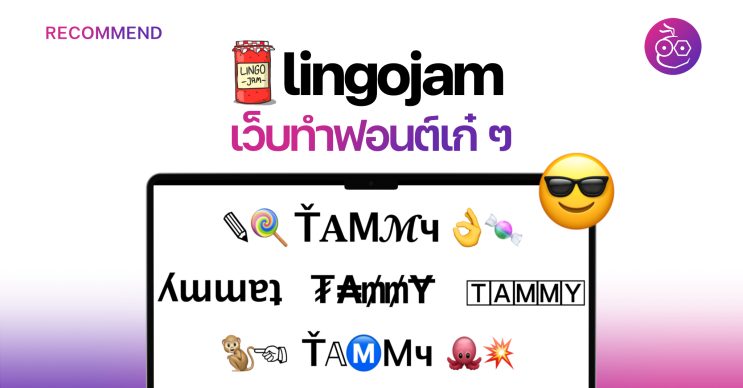
ใครที่เบื่อกับฟอนต์ตัวอักษรแบบเดิม ๆ ต้องลองใช้ lingojam เว็บนี้จะทำฟอนต์เก๋ ๆ ออกมาให้เราใช้ แถมยังดูแปลกใหม่สุด ๆ!
lingojam เว็บทำฟอนต์เก๋ ๆ ไว้ใช้!
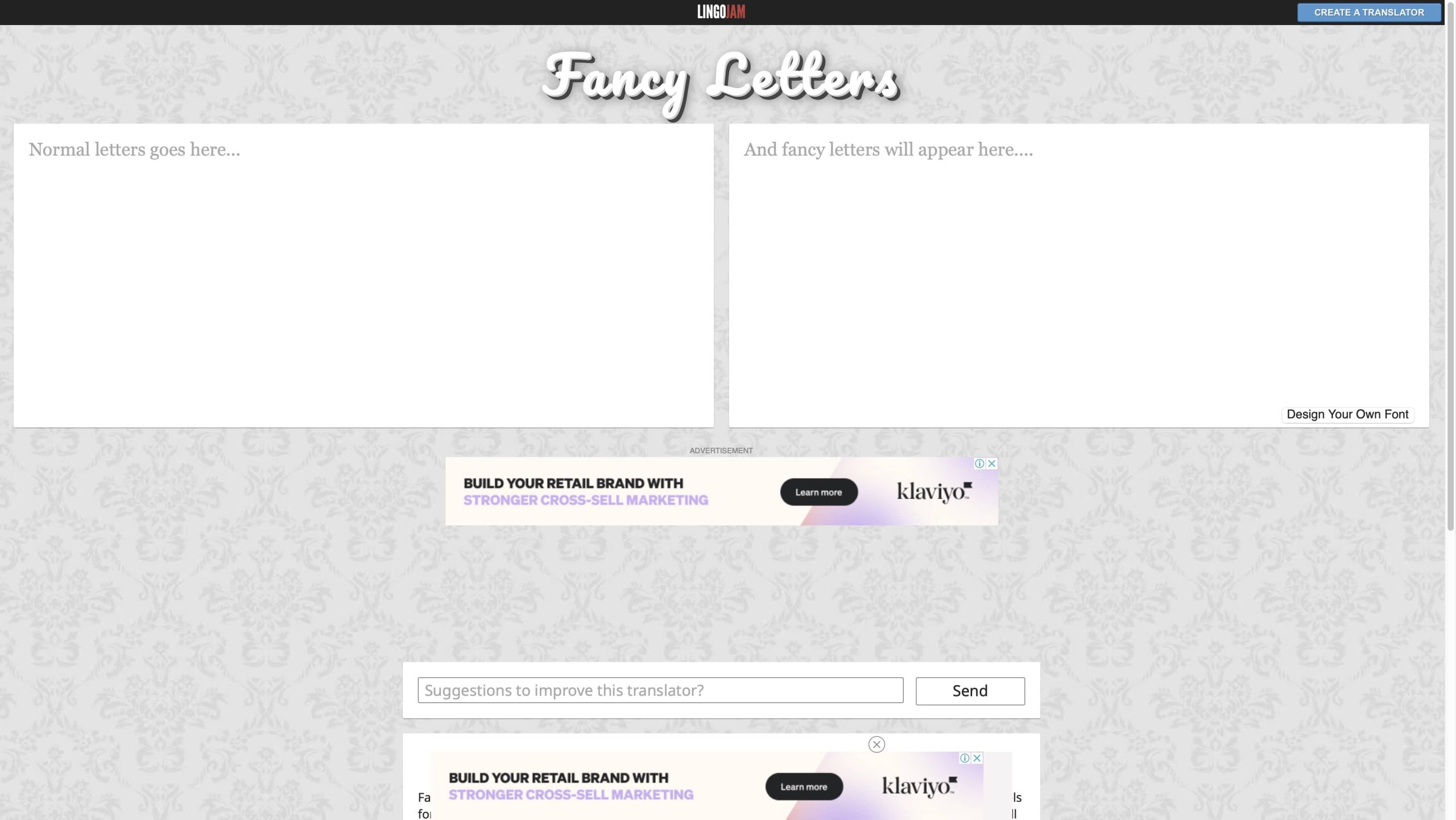
มาหน้าเว็บ lingojam ให้เราพิมพ์ข้อความที่ต้องการ
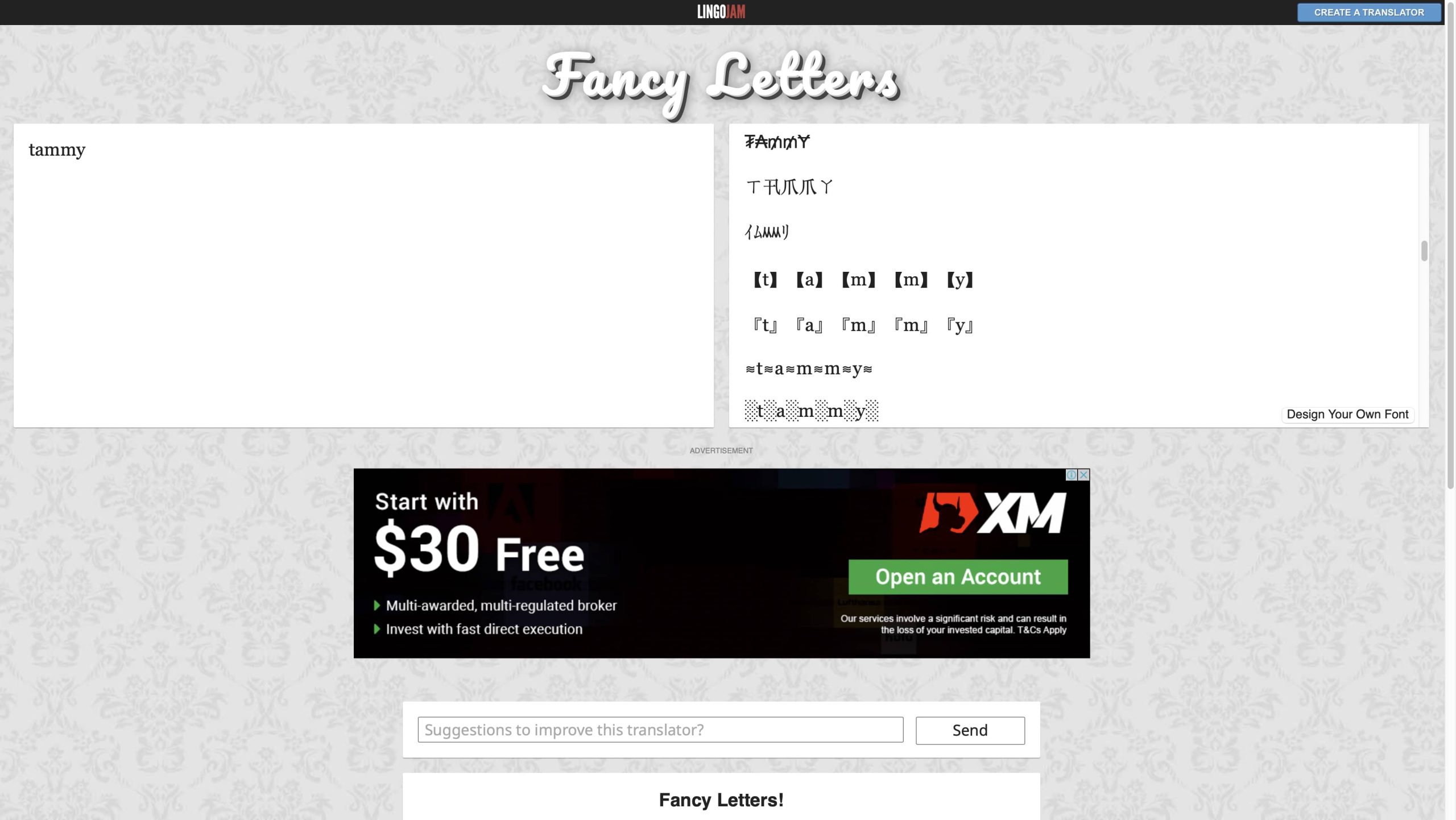
จากนั้นจะมีฟอนต์มากมาย ให้เราเลือก “Copy” แล้วนำไปใช้ได้เลย แล้วเว็บนี้ยังสามารถออกแบบฟอนต์เองได้ด้วย โดยกด “Design Your Own Font ” ด้านล่างขวาของฟอนต์ในเว็บ
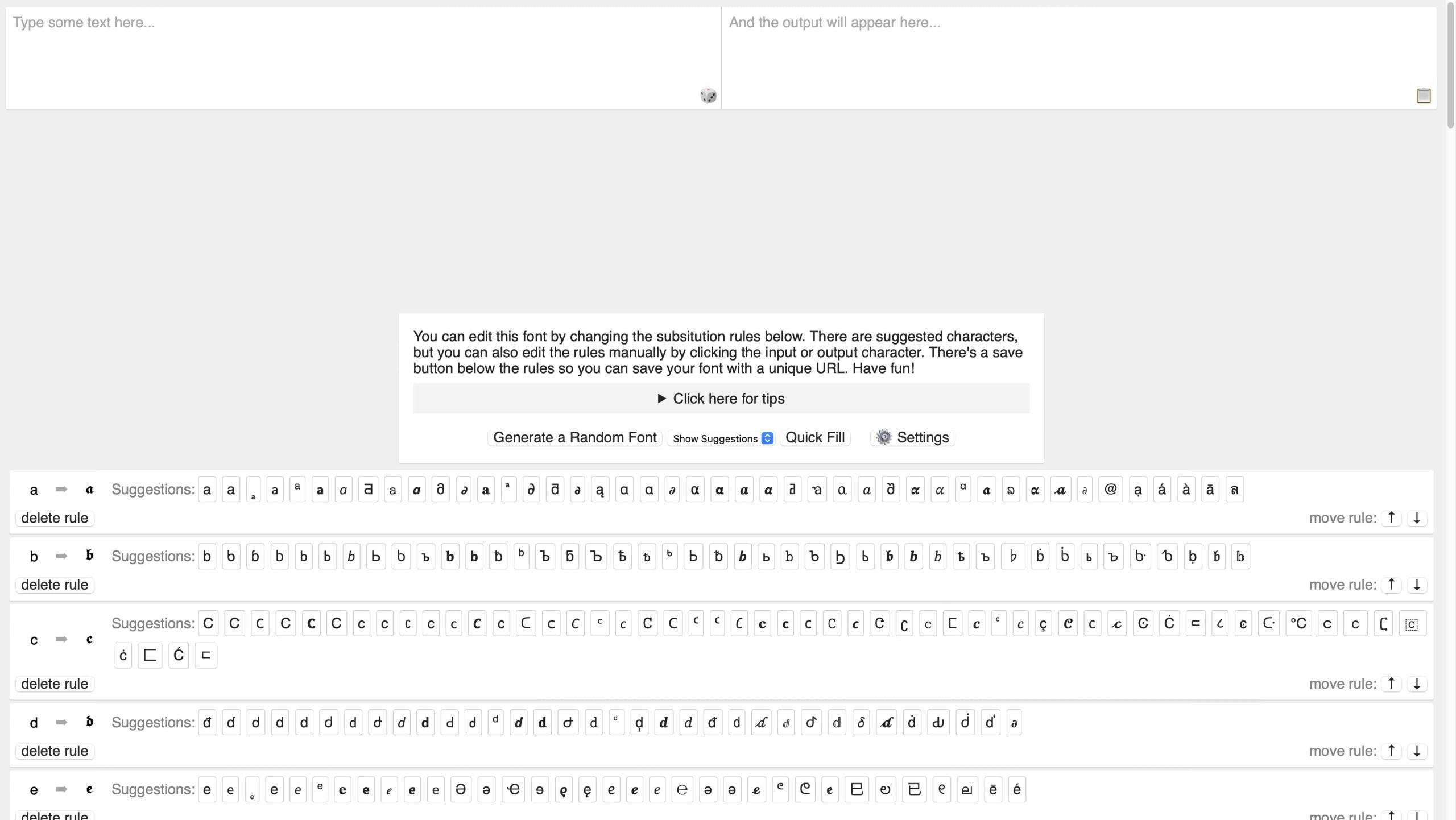
จะมาหน้าน้ีให้เราเลือกออกแบบตัวอักษรได้ตั้งแต่ A-Z เลยนะ นอกจากนี้เรายังกด “Generate a Random Font” ได้ถ้าต้องการสุ่มให้เว็บออกแบบตัวอักษรให้
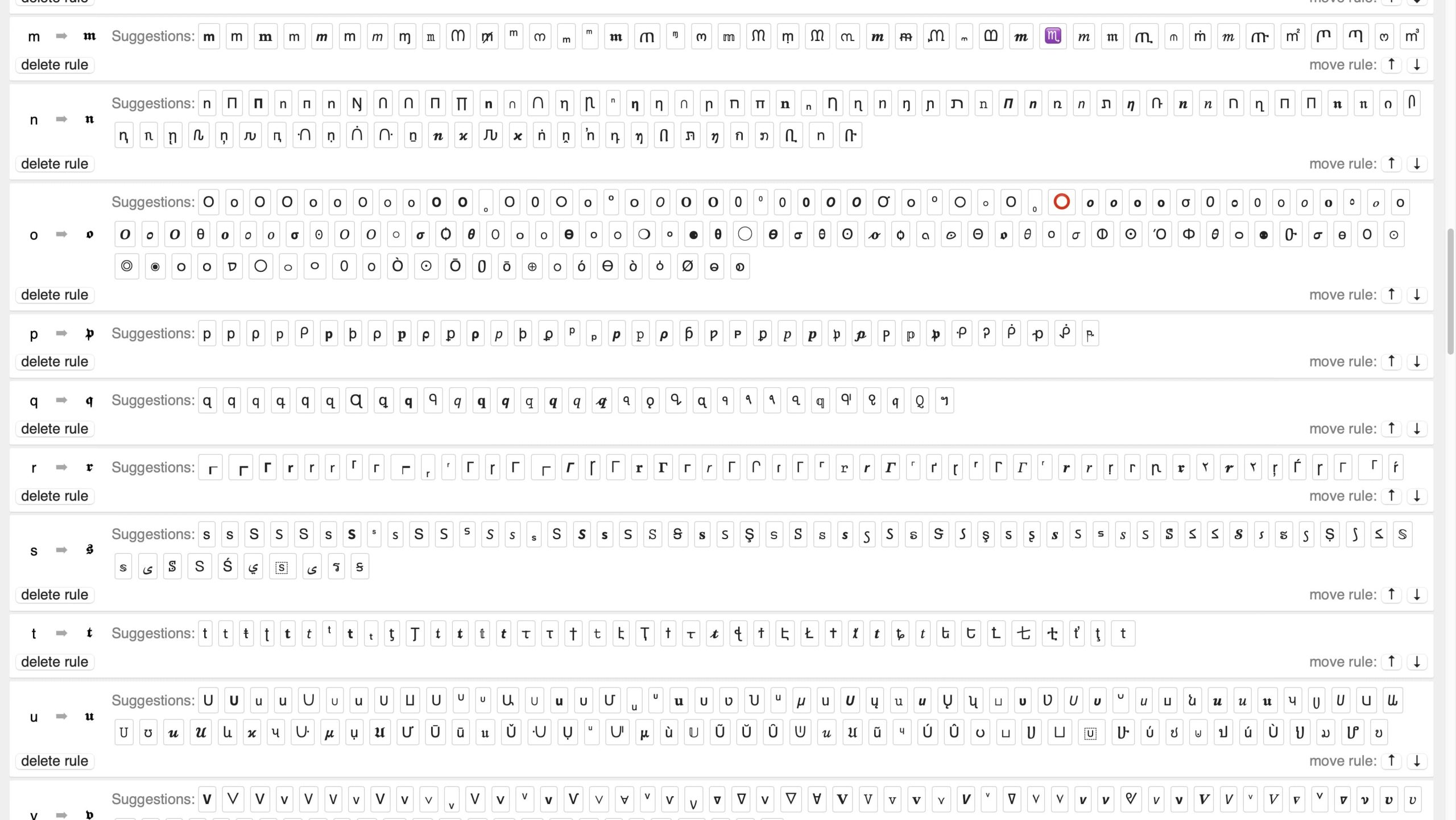
แล้วยังพิมพ์ข้อความด้านบน เพื่อดูฟอนต์ที่เราออกแบบเสร็จได้ด้วยนะ
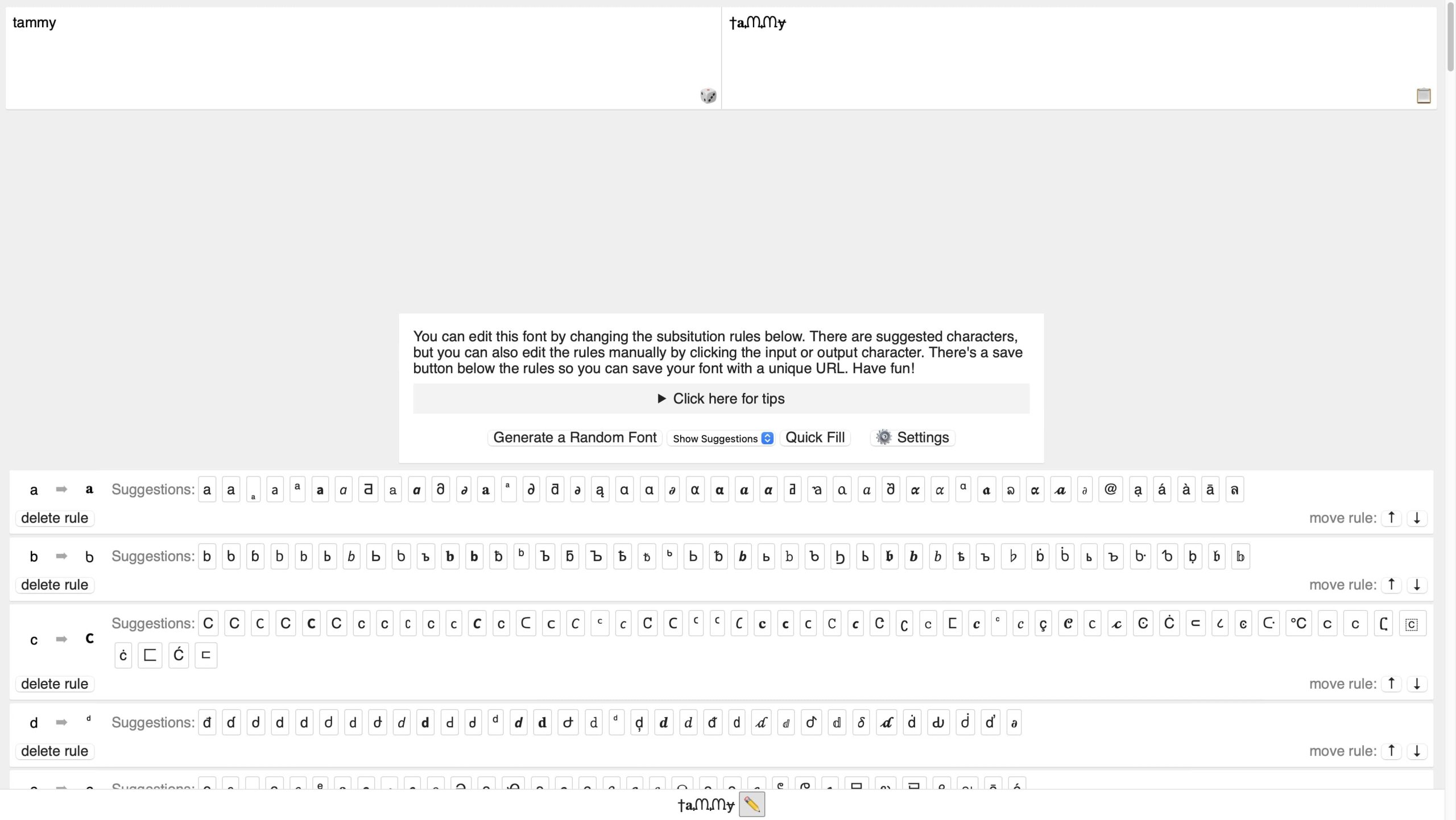
ตัวอย่างฟอนต์ในเว็บ
『t』『a』『m』『m』『y』
(っ◔◡◔)っ ♥ tammy ♥
✎🍭 Ť𝐀Μ𝓜ч 👌🍬
🐌 ⋆ 🐰 🎀 𝓉𝒶𝓂𝓂𝓎 🎀 🐰 ⋆ 🐌
ใครที่อยากได้ฟอนต์เก๋ ๆ แบบนี้ก็ไปใช้เว็บกันดู